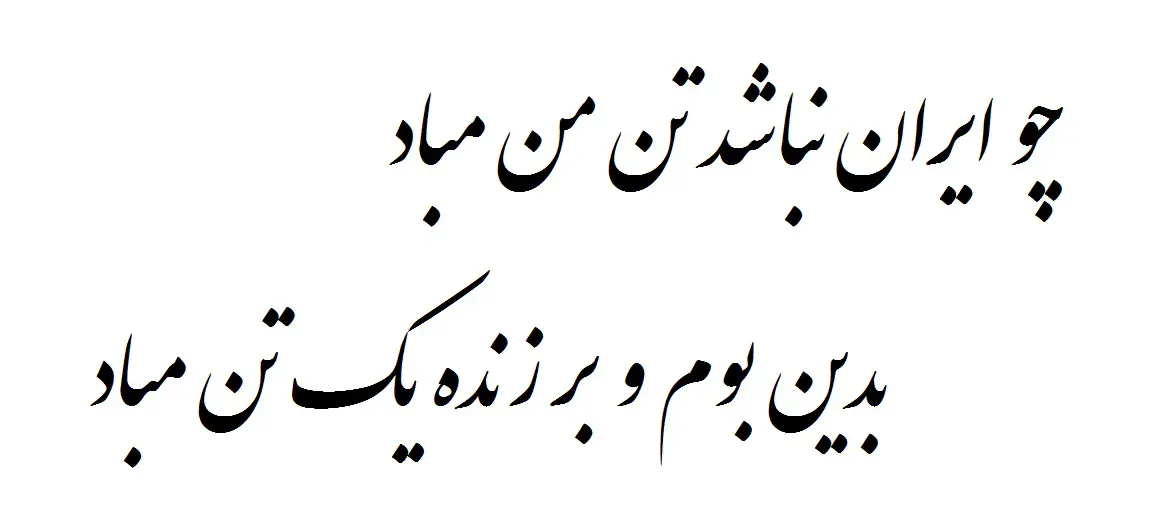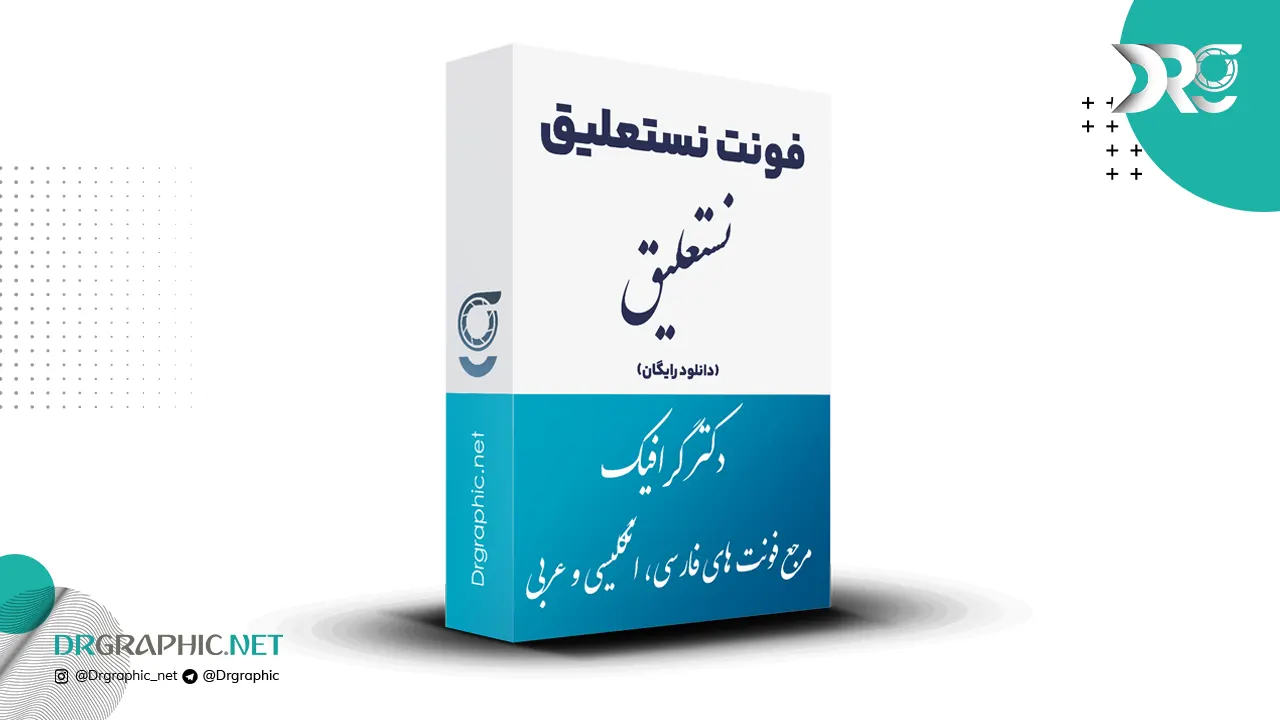
دانلود فونت نستعلیق Nastaliq
فونت نستعلیق Nastaliq
خط نستعلیق یکی از شیوه های نگارش خط است که ایرانی ها از دیرباز با خطاطی و خوشنویسی آن را در فرهنگ خود نگاه داشته اند . خط نستعلیق با توجه به تنوع ارتفاع قرارگیری حروف از خط مبنا یا خط کرسی نوشتاری، برای پیاده‌سازی و استفاده در ویراشگرهای متن مشکلات بسیاری ایجاد می‌کند و ترکیب‌های ممکن، تنوع را بی‌شمار می‌نماید.
نمونه نوشته با این فونت: